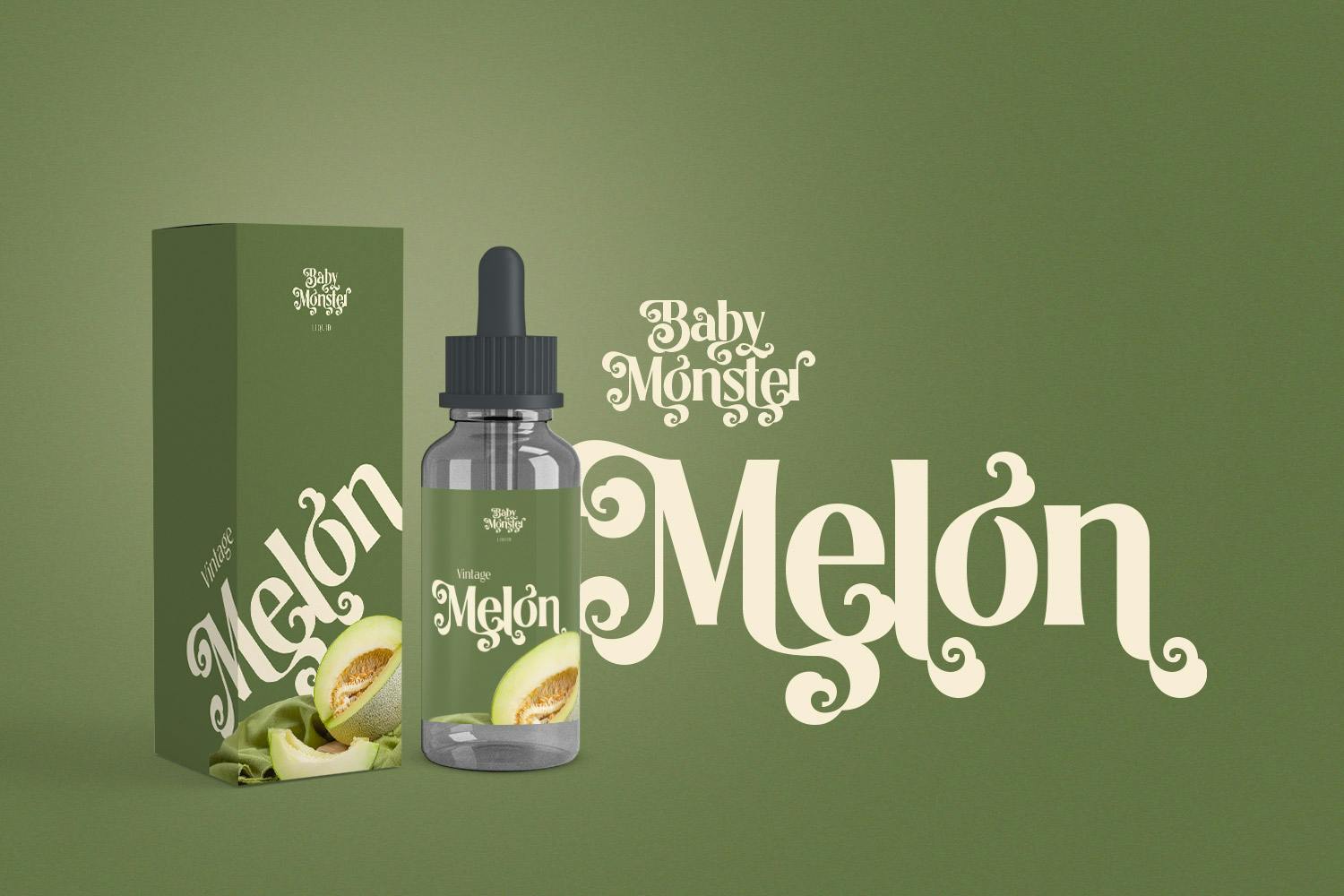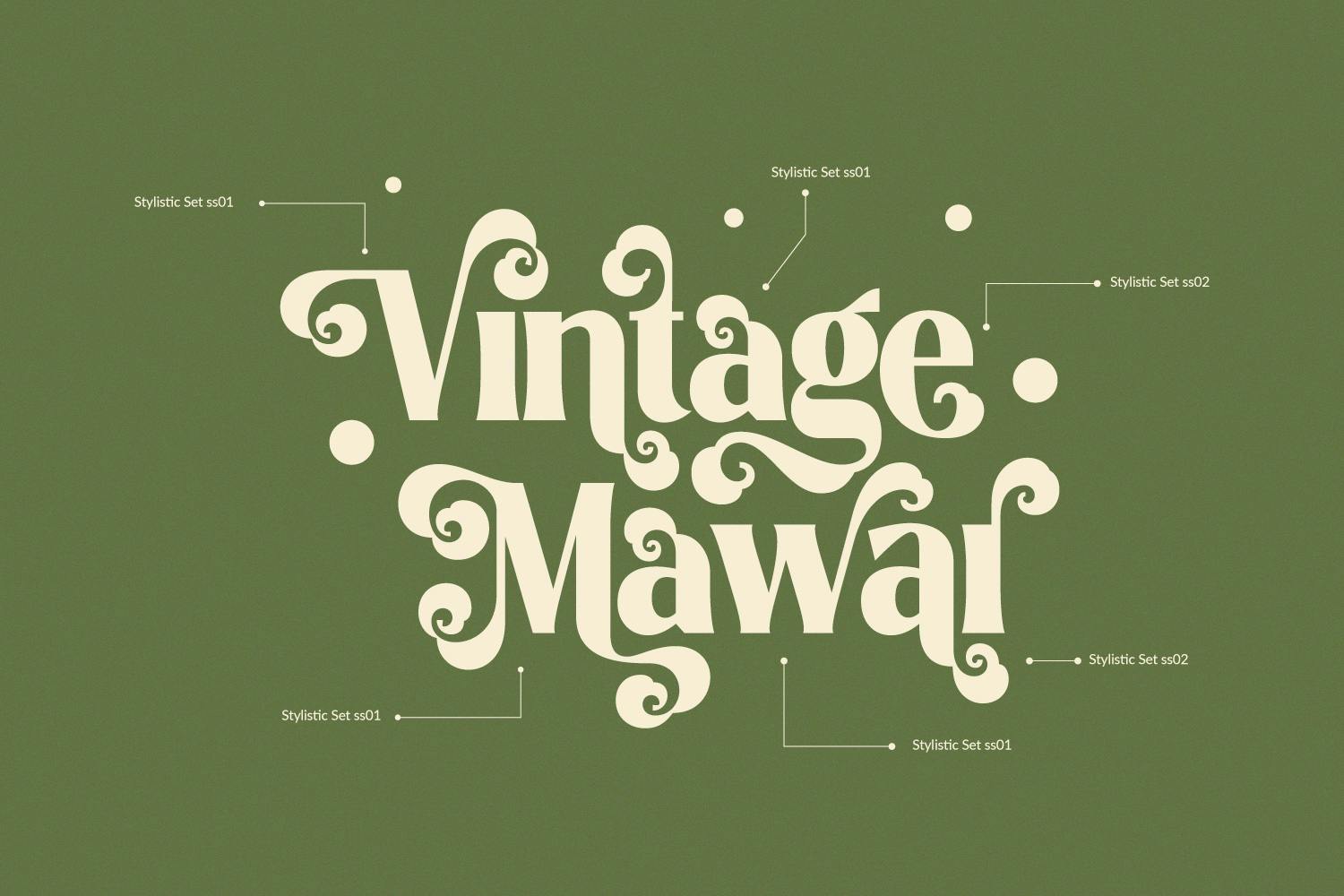
فونت True Sage یک خانواده زیبا و دکوری از فونتهای سریف است. این فونت با سبک وینتج و طراحی رمانتیک، دارای حروف متناوب زیبا و پیچیدهای است که باعث میشود نوشتهها جذاب و منحصر به فرد به نظر برسند. این فونت برای عنوانها، سرفصلها و پروژههای برندینگ شما بسیار مناسب است.